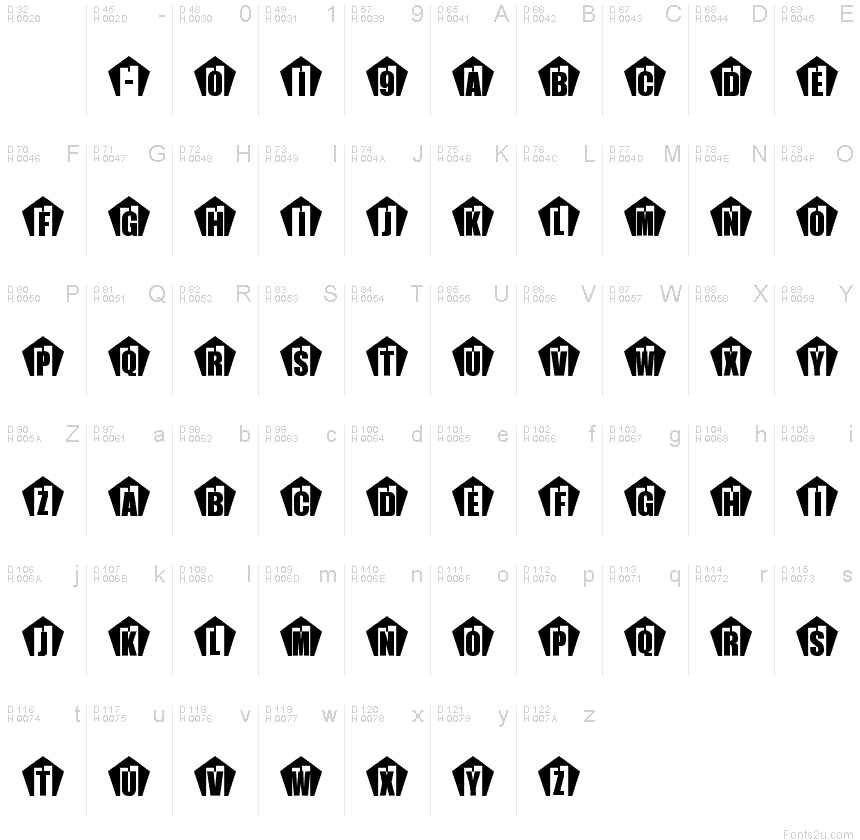
KR In Memory od Katfunfonts to darmowy, dekoracyjny krój pisma typu display. Każdy znak umieszczony jest wewnątrz wysokiej, przypominającej trumnę ramki, z wyrazistymi czarnymi kształtami i jasnymi białymi wcięciami, które kojarzą się z rzędem nagrobków oświetlonych świecami. Masywne, skondensowane litery tworzą ciasny, niemal klaustrofobiczny rytm, który natychmiast nadaje mroczny, upiorny klimat bez konieczności dodawania dodatkowej grafiki.
KR In Memory pozwala stworzyć świetne tytuły na ulotki na Halloween, plakaty domów strachów, horrory, zaproszenia na imprezy, pamiątkowe albumy czy niepokojące grafiki do mediów społecznościowych. Ten darmowy font najlepiej prezentuje się w dużym rozmiarze, gdy sylwetki trumien są wyraźnie widoczne; do tekstu uzupełniającego dobierz prosty bezszeryfowy krój, aby wyraziste ikony pozostały na pierwszym planie.